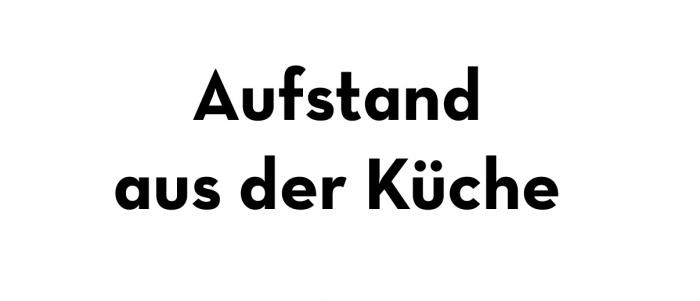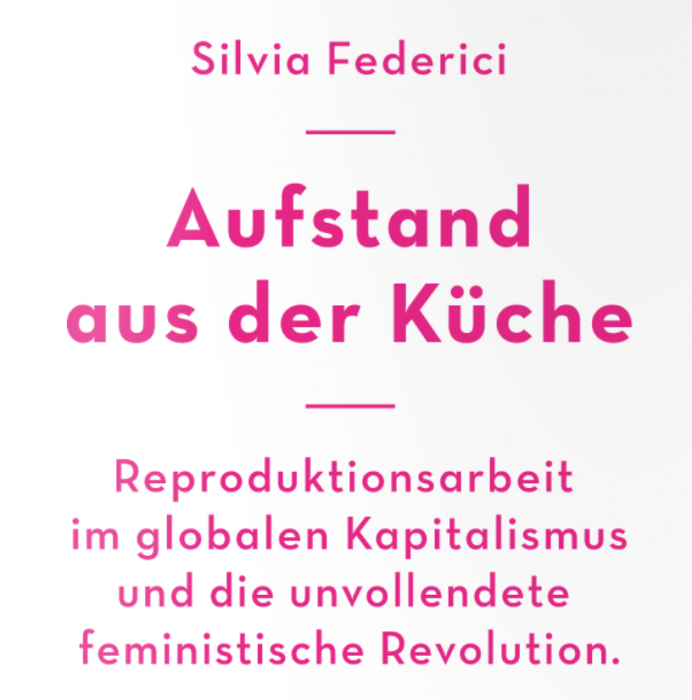
Welche Schrift / Futura-Variante(?) ist das?
ich wollte gerne wissen, welche Schrift für den Titel dieses Buches (2012) verwendet wurde:
Für mich sieht es nach einer leicht veränderten Futura aus, mit einigen Abweichungen – s. vor allem das große R und F mit den großen Oberlängen(?).
P.S: WhatTheFont und myfonts-Durchstöbern habe ich natürlich schon hinter mir - leider erfolglos.
Hallo, ja, auf Anhieb an den Versalien. Neutraface habe ich sozusagen "auf dem Zettel" - gefällt mir ausnehmend gut.